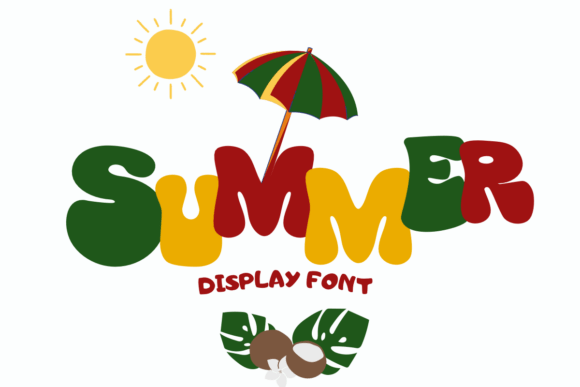
Summer
Summer Display Font: A Fonte que Transforma Seu Projeto em Verão Perpétuo
Se você está buscando uma fonte tropical que traga energia, alegria e aquele toque de sunny vibes para seus designs, a Summer Display Font é a escolha perfeita. Inspirada nos dias ensolarados à beira-mar, ela combina formas robustas e divertidas com cores vibrantes de ilha, garantindo que cada palavra pareça feita de areia dourada e ondas azuis.
- Design ousado e divertido: Letras grossas e cheias, ideais para chamar a atenção em cartazes, capas de revistas e anúncios de verão.
- Paleta de cores vibrante: Disponível em tons tropicais que dão vida instantânea a qualquer projeto, seja em papel ou digital.
- Versatilidade de uso: Perfeita para promoções de verão, roupas infantis, posters de férias e branding lúdico.
- Legibilidade garantida: Mesmo com seu estilo descontraído, a fonte mantém clareza em tamanhos pequenos e grandes.